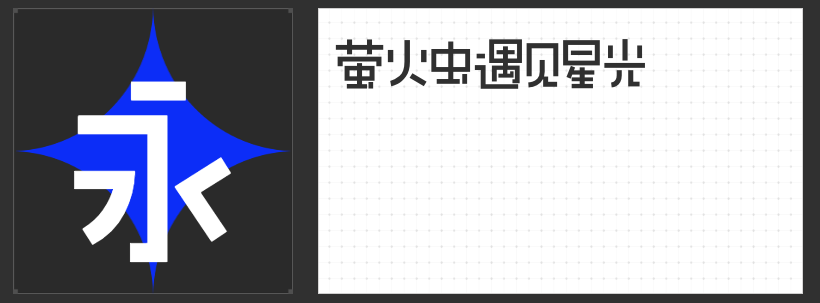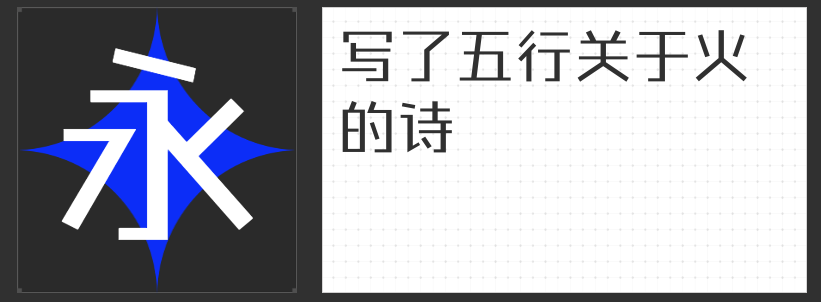
四款包装设计专属字体:以形传意,重塑品牌视觉魅力
在包装设计的世界里,字体不仅是信息传递的载体,更是品牌性格的直观表达。一款契合的字体能瞬间抓住消费者目光,赋予产品独特的记忆点。以下四款字体各具风格,从灵动俏皮到稳重现代,为包装设计注入多元美学基因。
一、励字敲可爱简 常规
这款字体以手写圆润线条为基底,通过省略部分笔画与简化结构,营造出“用心书写”的随性美感。略带俏皮的直线设计打破传统手写体的柔弱感,在保留辨识度的同时,传递出温暖、治愈的视觉情绪。其独特的“不完美”笔触,适合儿童食品、文创礼品或手作品牌的包装,能快速拉近与消费者的情感距离。
二、字恋狂澄空 迟风
以“上松下紧”的重心布局与灵活多变的字型结构,赋予字体动态韵律感。笔画粗细均匀,弧线与直线交融,平直切角处理减少锐度,搭配“断开”的笔画留白,整体轻盈而不失力量。这种设计既保留了手写体的自然气息,又通过理性布局提升视觉秩序感,适用于咖啡、茶饮或轻奢零食的包装,传递自由、随性的生活态度。
三、励字钧线黑简 常规
全直线设计搭配精准斜度与利落转折,以几何美感重构黑体形态。摒弃冗余装饰,通过细节优化降低阅读障碍,同时以棱角分明的轮廓传递坚定、果敢的品牌态度。其强烈的视觉冲击力适合科技产品、运动装备或男性护肤品的包装,在货架陈列中能迅速脱颖而出,成为画面焦点。
四、励字志向黑简 中粗
融合圆体与黑体的双重基因,通过外圆角处理软化传统黑体的生硬感,在稳重结构中注入灵动气息。字面充实、结构稳定的设计适配屏显场景,同时中粗笔画强化了实体包装的质感呈现。这款字体适用于高端食品、家居用品或美妆产品的包装,传递可靠性与精致感并存的视觉语言。
从手写温度到几何棱角,从灵动节奏到刚柔平衡,这四款字体以多元风格满足不同品类的包装需求,助力品牌在视觉竞争中脱颖而出。